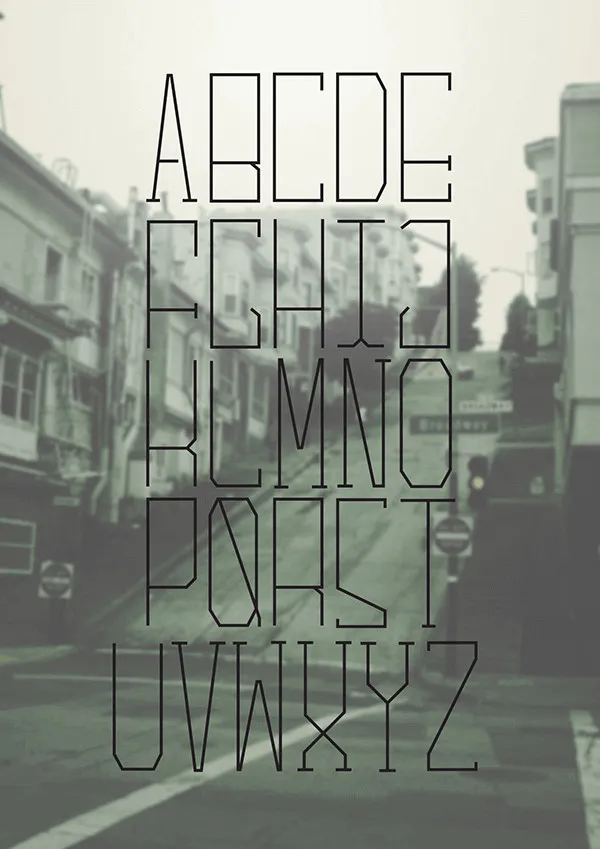
Downtown font
A Downtown font é o primeiro projeto do designer Filipe Rolim no campo da tipografia. Desenvolvida pelo próprio designer Hamilton, a Downtown oferece uma experiência visual vibrante e atemporal para projetos digitais modernos. Com suas cores vibrantes, linhas robustas e um leque de caracteres inclusivo que inclui maiúsculas com sublinhados, números e símbolos, a Downtown font é perfeita para criar ambientes urbanos emocionantes e inovadores. Para aqueles apaixonados por uma tipografia forte e dinâmica que vai ao encontro da essência de uma cidade vibrante, essa fonte é certamente o item de desejo do seu portfolio.